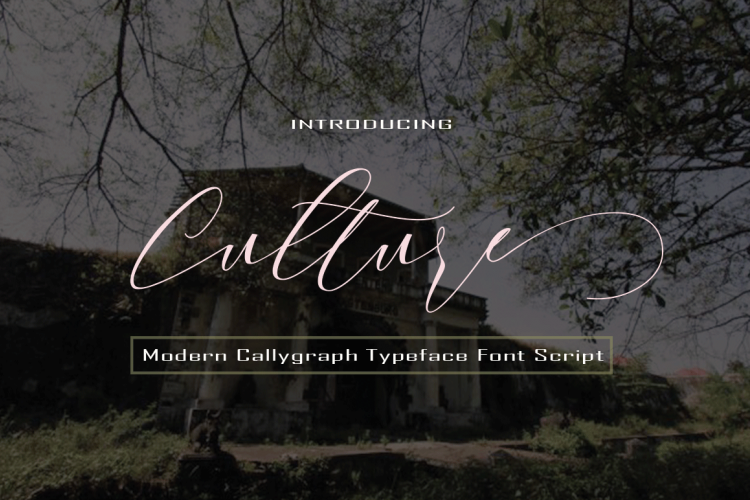
Culture Script Font – Download Grátis
Bem-vindo à Culture Script Font, uma proposta única e elegante para estiloscript tipográfico moderno. Essa fonte foi criada pelo 24Design com uma base de linhas variável que inclui linhas finas e toques clássicos e elegantes. Ela é perfeita tanto para projetos criativos quanto para aplicações específicas, como títulos, assinaturas, logotipos, cartões de convite de casamento, camisetas, guias de endereçamento, placas, rótulos e até mesmo para noticiários e postais. Cultura Script é a escolha perfeita para dar um toque sofisticado em seu próximo projeto gráfico. Não deixe de experimentar essa fonte moderna e elegante.